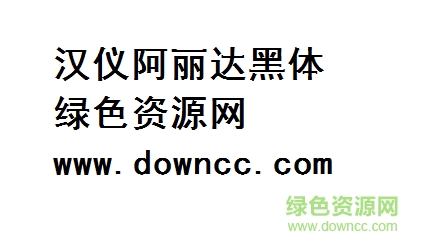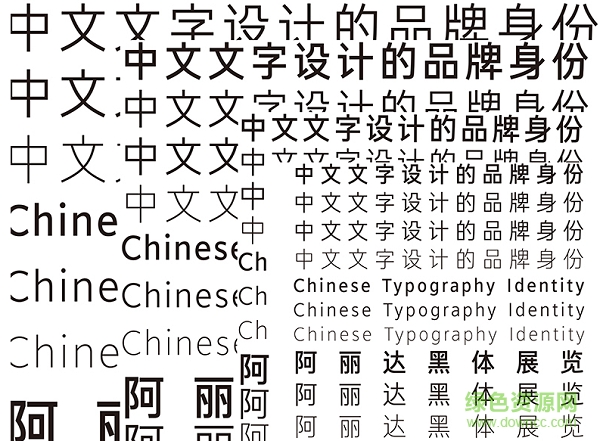
漢儀阿麗達(dá)黑體是一款非常實(shí)用的印刷設(shè)計(jì)黑體,該字體整體風(fēng)格得體大方,用于標(biāo)題和內(nèi)容的設(shè)計(jì)非常醒目,十分養(yǎng)眼,有需要的朋友歡迎到綠色資源網(wǎng)下載!
阿麗達(dá)(Arita)黑體是韓國(guó)世界著名化妝品企業(yè)愛茉莉太平洋(AMOREPACIFIC)集團(tuán)與漢儀字庫(kù)公司合作定制的一款品牌專用印刷字體。由韓國(guó)著名設(shè)計(jì)師安尚秀、中央美術(shù)學(xué)院教授王子源設(shè)計(jì)指導(dǎo),漢儀字庫(kù)高級(jí)字體設(shè)計(jì)師劉宇、張暄設(shè)計(jì)完成。“窈窕淑女”“、亭亭玉立”、“氣韻生動(dòng)” 是愛茉莉太平洋所追求并塑造的、亞洲經(jīng)典女性之美的簡(jiǎn)要概括,這也成為此次品牌字體設(shè)計(jì)的原則和標(biāo)準(zhǔn)。